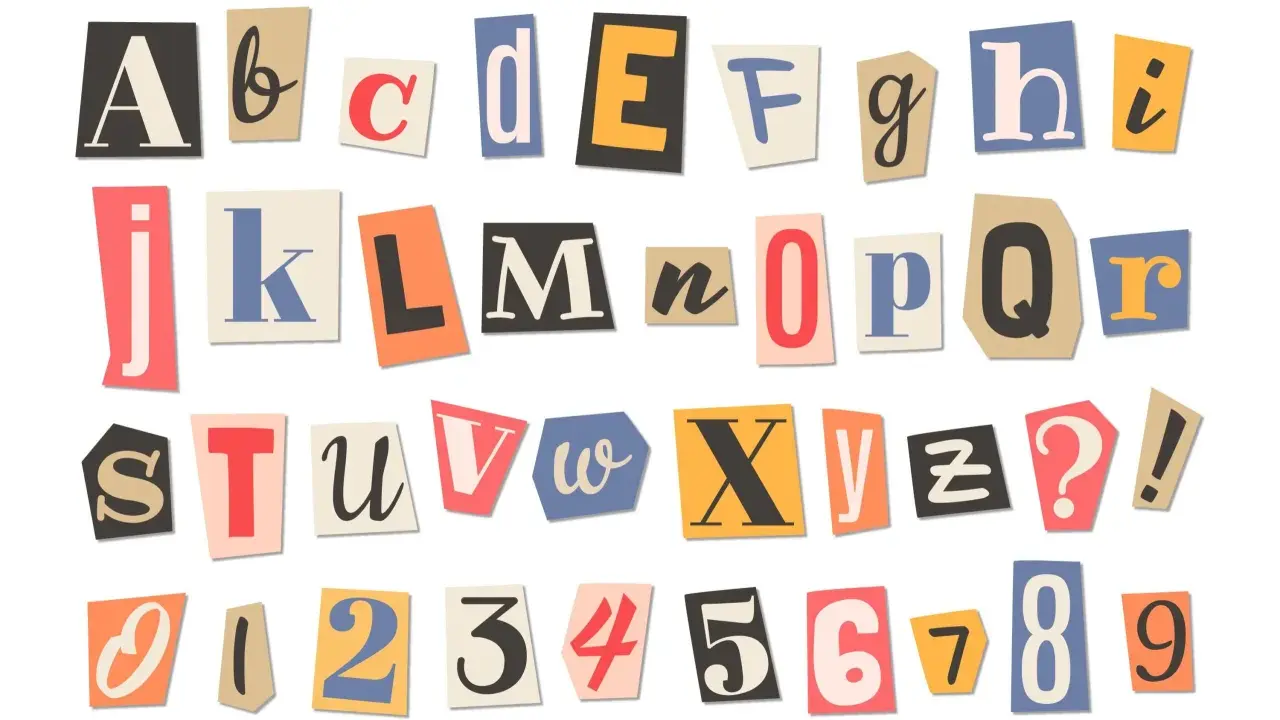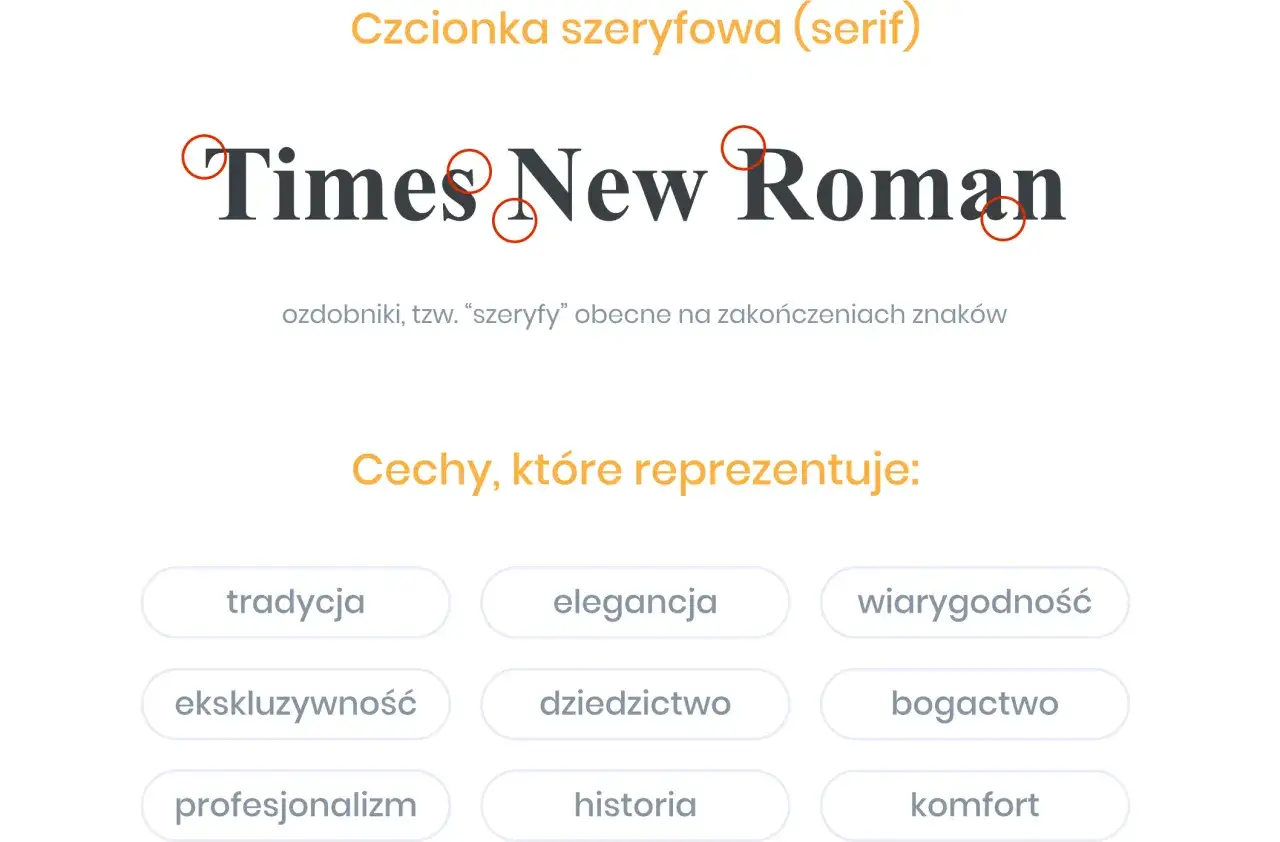
Czcionki liter - Jak je dobrać, by projekt zachwycał?
Kolaż liter i cyfr, jak wycięte z gazet. Różnorodne czcionki liter tworzą alfabet od A do Z, a także cyfry od 0 do 9.
Dobrze dobrane czcionki liter wpływają na to, czy projekt wygląda profesjonalnie, czy tylko dekoracyjnie. W praktyce liczy się nie tylko styl, ale też czytelność, dopasowanie do marki, obsługa polskich znaków i to, jak tekst zachowuje się na ekranie telefonu. Poniżej porządkuję temat bez zbędnej teorii: od podstawowych pojęć, przez dobór kroju, po błędy, które najczęściej psują cały efekt.
Najważniejsze zasady, które warto zapamiętać od razu
• W typografii najważniejsze są czytelność, hierarchia i dopasowanie do celu, a nie sam efekt „ładnego fontu”.
• Krój pisma, font i potoczna „czcionka” to nie zawsze to samo, więc warto używać tych pojęć świadomie.
• Najczęściej wystarczą dwie rodziny pisma: jedna do nagłówków, druga do tekstu głównego.
• Przy polskich projektach trzeba sprawdzić diakrytyki, licencję i wygląd na mobile.
• Odbiór tekstu równie mocno psują źle ustawione odstępy, kontrast i interlinia, co sam wybór kroju.
• W 2026 roku najlepiej pracują kroje elastyczne, lekkie technicznie i spokojne wizualnie.
Czcionka, krój pisma i font to nie to samo
W codziennej rozmowie te słowa mieszają się bez większego problemu, ale w projektowaniu warto je rozróżniać. Krój pisma to projekt liter, font to jego cyfrowa postać lub konkretna odmiana, a „czcionka” bywa używana potocznie na określenie całego zestawu. Ja zwykle zwracam na to uwagę wtedy, gdy ktoś mówi „potrzebuję ładnej czcionki”, bo za tym zdaniem często kryje się niejedno pytanie: czy chodzi o styl, grubość, czytelność, czy o sam plik do wdrożenia.
To rozróżnienie ma znaczenie także przy zamawianiu projektu. Jeśli ustalisz, że potrzebujesz rodziny pisma z kilkoma wagami, unikniesz później nieporozumień typu „mieliśmy jedną czcionkę, a wyszły trzy różne style”. W praktyce projektowej chodzi więc nie o pojedynczy znak, ale o cały system: nagłówki, tekst podstawowy, akcenty i warianty techniczne. Gdy to uporządkujesz, łatwiej przejść do tego, jakie kroje realnie sprawdzają się w różnych zadaniach.
Czcionka szeryfowa Times New Roman, z ozdobnikami liter, symbolizuje tradycję, elegancję i profesjonalizm.
Jakie kroje pisma pasują do różnych zadań
Nie ma jednego „najlepszego” kroju. Inaczej pracuje się nad artykułem, inaczej nad landing page’em, a jeszcze inaczej nad identyfikacją wizualną dla marki premium. W praktyce dobrze działa proste pytanie: czy ten font ma prowadzić treść, czy ma sam być częścią komunikatu.
Krój Charakter Najlepsze zastosowanie Na co uważać
Serif Klasyczny, redakcyjny, bardziej „literacki” Dłuższe teksty, editorial, marki premium, publikacje eksperckie W małych rozmiarach może wyglądać zbyt delikatnie
Sans serif Neutralny, nowoczesny, uporządkowany Strony internetowe, UI, prezentacje, e-commerce, komunikacja marki Bez dobrego projektu bywa zbyt bezosobowy
Slab serif Mocny, wyrazisty, z cięższymi zakończeniami Nagłówki, plakaty, branding z charakterem Nie jest najlepszy do długich bloków tekstu
Display Ozdobny, ekspresyjny, zapamiętywalny Logotypy, kampanie, opakowania, krótkie hasła Szybko męczy, jeśli użyjesz go zbyt często
Script / handwritten Osobisty, emocjonalny, ręcznie pisany w odbiorze Zaproszenia, akcenty, projekty lifestyle’owe Łatwo traci czytelność, szczególnie na ekranie
Monospace Techniczny, precyzyjny, rytmiczny Code, dane, projekty technologiczne, detale informacyjne Nie nadaje się do długiej, ciągłej lektury
W polskich projektach testuję dodatkowo wszystkie znaki z ogonkami i kreskami: ą, ę, ł, ś, ź, ż, ć, ń. Ozdobny krój może wyglądać świetnie w angielskim podglądzie, a potem rozpaść się właśnie na tych literach, które są dla nas codziennością. Gdy już wiesz, który typ kroju ma sens, trzeba przejść do wyboru dopasowanego do marki i kanału komunikacji.
Jak dobrać krój do marki, treści i kanału
Ja zwykle zaczynam od trzech pytań: co ma poczuć odbiorca, gdzie będzie czytał tekst i jak długo ten kontakt potrwa. Innego kroju potrzebuje komunikat reklamowy, a innego raport, blog ekspercki albo strona produktowa. System typograficzny działa lepiej niż pojedynczy „ładny font”, bo daje spójność w całym projekcie.
1. Określ rolę tekstu. Jeśli to treść użytkowa, stawiam na prostotę. Jeśli to element wizerunkowy, mogę pozwolić sobie na więcej charakteru.
2. Dobierz jedną rodzinę do treści i jedną do nagłówków. Więcej to nie zawsze lepiej. Najczęściej dwie dobrze dobrane rodziny wystarczają.
3. Sprawdź ton marki. Kancelaria, marka medyczna i startup technologiczny nie powinny mówić typografią w ten sam sposób.
5. Testuj na realnym materiale. Nagłówek, akapit, CTA, podpis pod zdjęciem i wersja mobilna pokażą więcej niż pojedyncza próbka alfabetu.